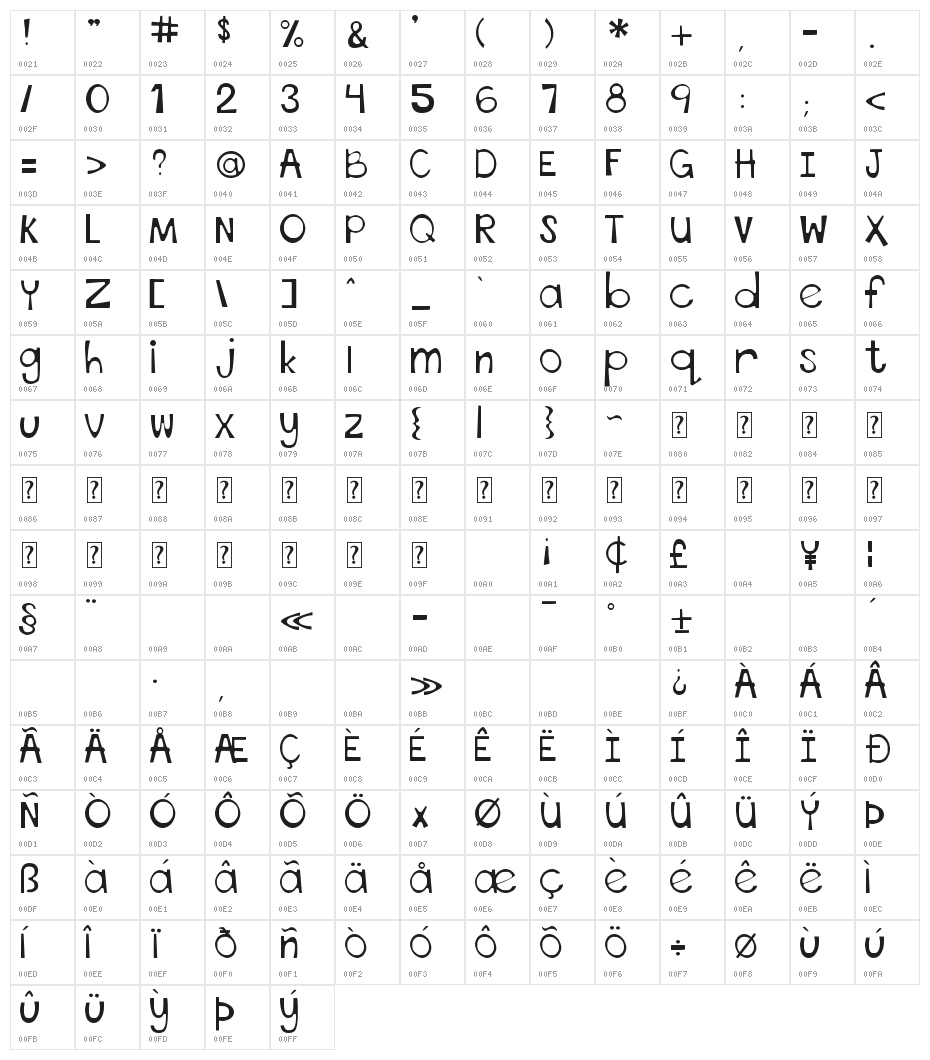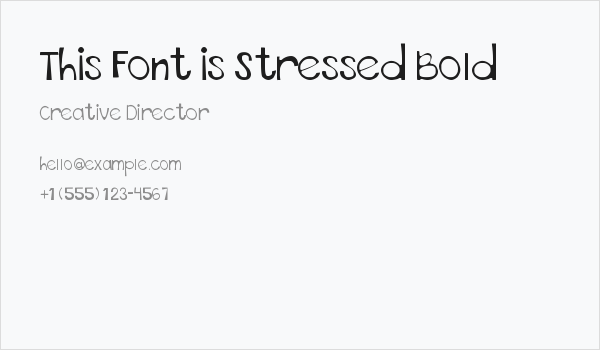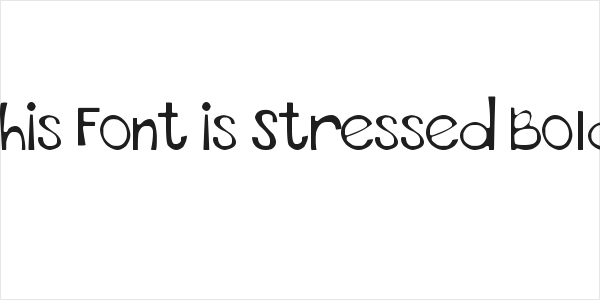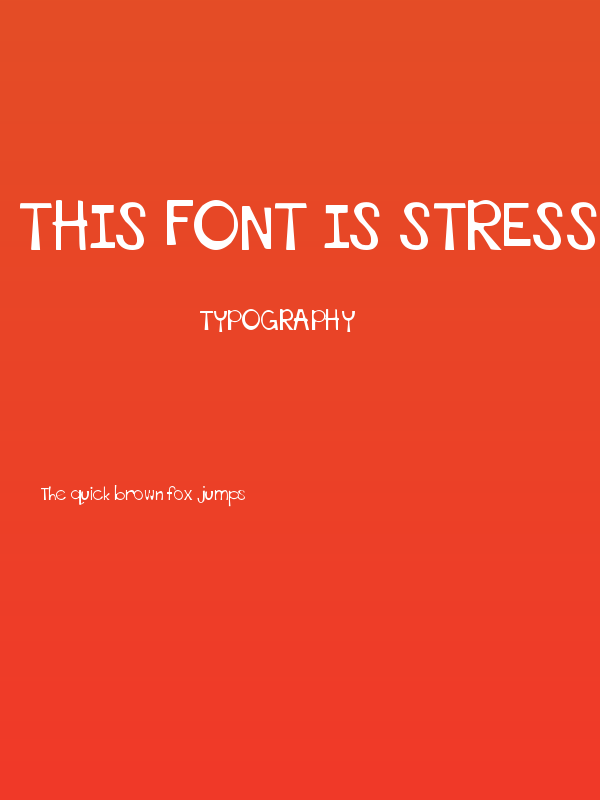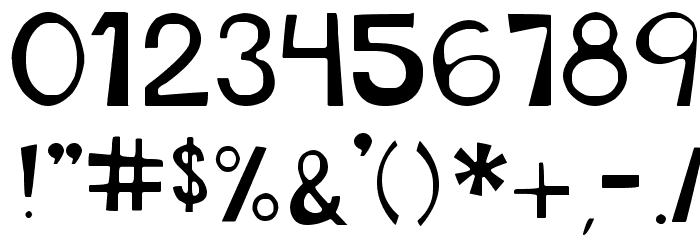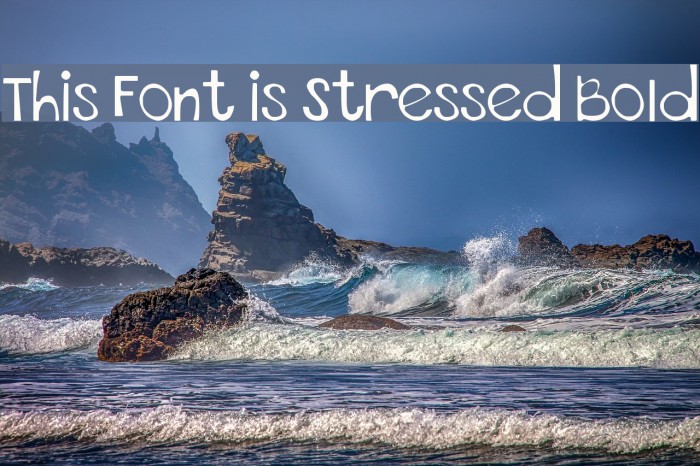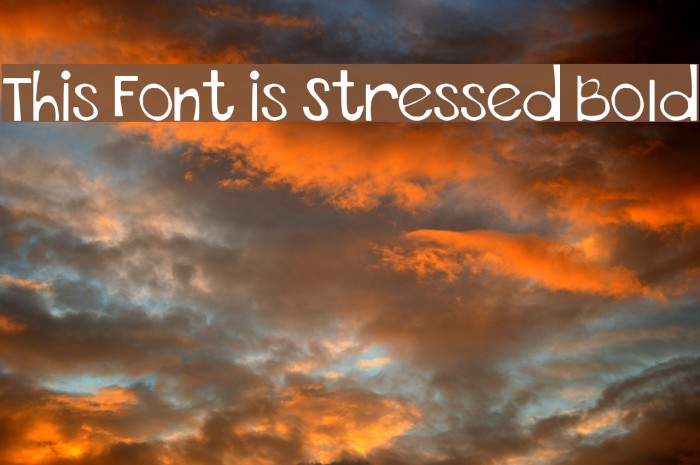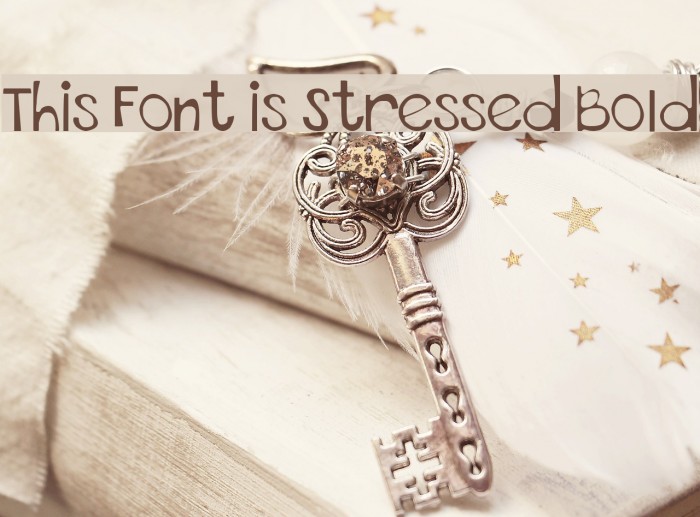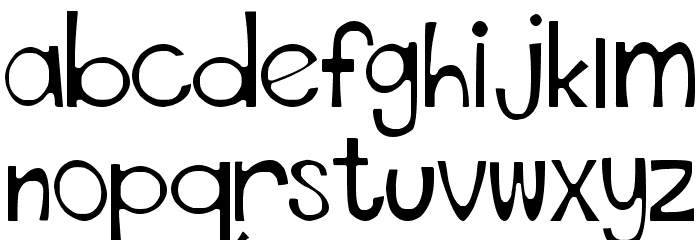
This Font is Stressed Bold Font
| Estilo general | Playful, Whimsical |
| Proyectos propuestos | Ideal for children's books, playful branding, party invitations, and creative posters. |